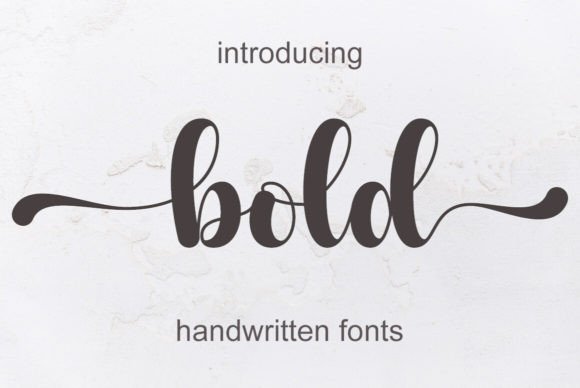
Bold
Bold : La police manuscrite qui allie élégance et modernité
Vous cherchez une police qui transforme chaque projet en une véritable œuvre d’art ? Bold est la réponse. Ce style d’écriture manuscrite, à la fois stylé et incroyablement élégant, séduit les designers pour sa capacité à sublimer invitations, cartes de remerciement, citations, cartes de vœux, logos, cartes de visite et bien plus encore.
Pourquoi choisir Bold pour vos créations ?
- Esthétique raffinée : ses courbes fluides et ses traits délicats apportent une touche sophistiquée à chaque support.
- Polyvalence exceptionnelle : parfaite pour les wedding invitations, les cartes de remerciement, les citations inspirantes, les cartes de vœux, les logos d’entreprise et les cartes de visite.
- Gain de temps : les alternates intégrés permettent de varier les ligatures et les styles d’écriture en un clic, évitant ainsi les recherches fastidieuses.
Expérience utilisateur : un confort de création inégalé
Bold a été conçue avec une attention particulière aux détails typographiques. Chaque lettre possède des espacements optimisés, garantissant une lecture fluide même à petite taille. De plus, la police reste nette et lisible sur les supports numériques comme sur le papier, ce qui la rend idéale pour les impressions de haute qualité.
Conclusion
Que vous soyez graphiste professionnel, organisateur de mariages ou entrepreneur souhaitant créer une identité visuelle unique, Bold est la police manuscrite qui donne du caractère à chaque création. Son élégance, sa polyvalence et sa facilité d’utilisation en font un incontournable pour tous vos projets design.